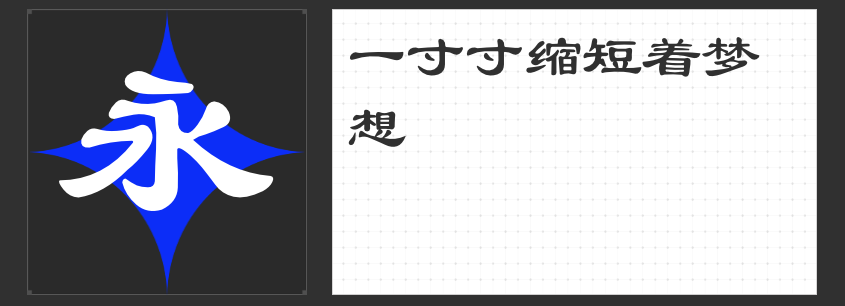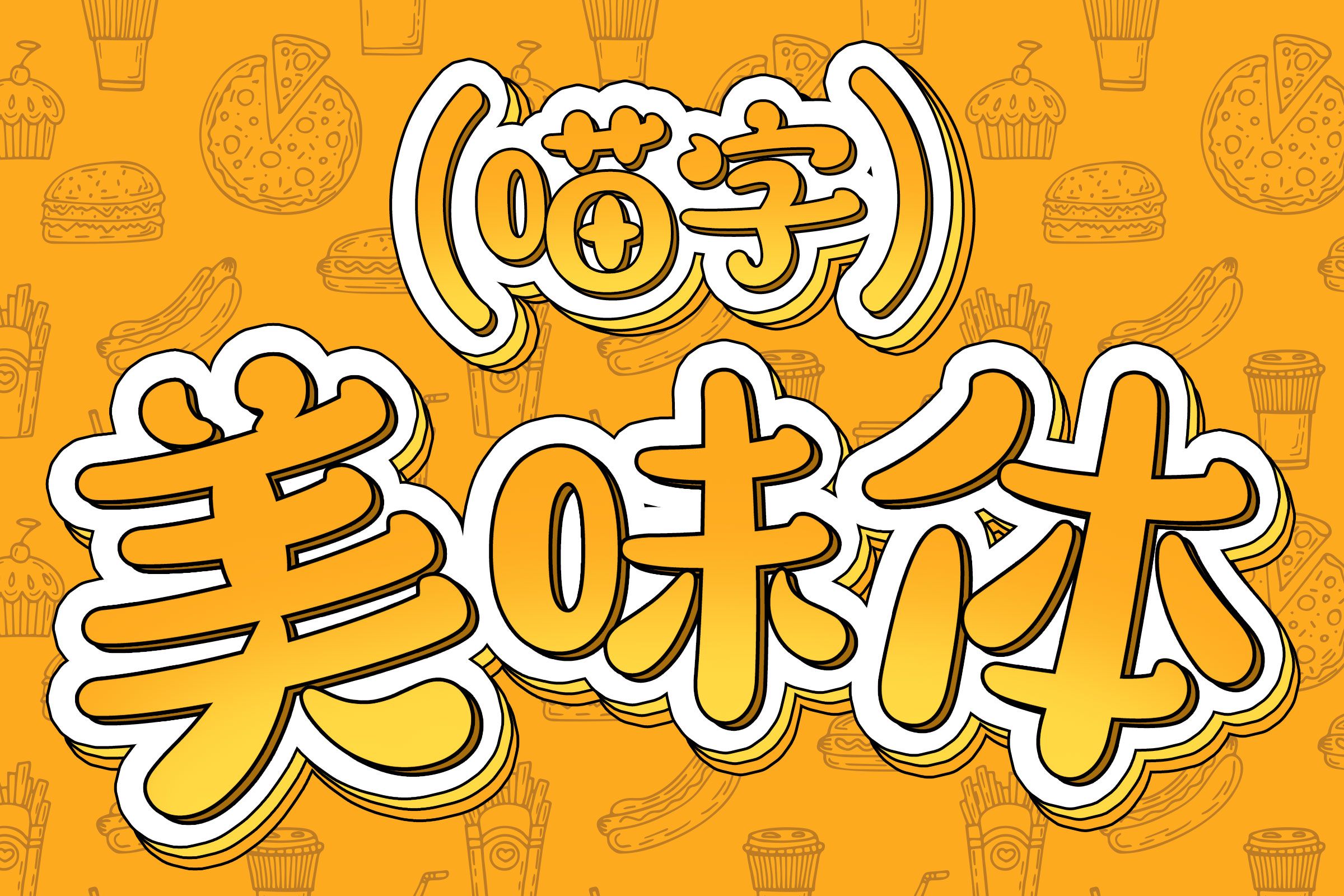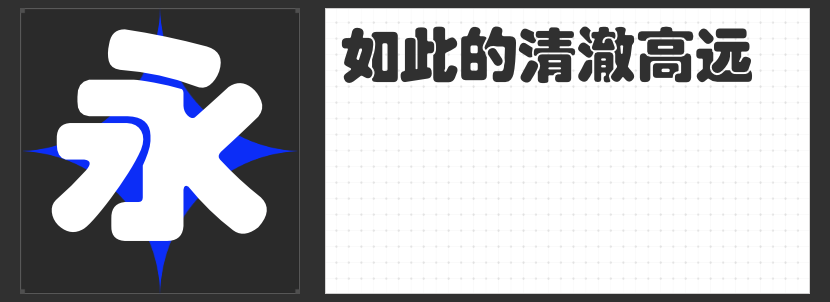
招牌设计的视觉密码:四款风格化字体赋能商业空间
招牌是商业空间的第一张名片,其字体选择直接影响品牌记忆度与空间氛围营造。本文精选四款兼具艺术张力与功能适配性的专业字体,从传统书韵到现代创意,为不同业态的招牌设计提供多元解决方案。
一、励字舒体简繁
这款融合五体书风与颜柳筋骨的创意字体,以0.8:1的字面率构建出独特的视觉韵律。其笔画粗细对比达1:3.5,在保持传统书法韵味的同时,通过现代参数化设计优化了远距离识别性。特别适合茶文化空间、文创书店等场景。
二、喵字美味体
专为美食空间开发的圆润字体,通过0.6pt的圆角半径处理与15°的笔画倾斜角,创造出类似食物饱满形态的视觉联想。其字怀(笔画内部空间)比常规字体扩大20%,在较远观看距离下仍保持清晰可读性。
三、励字琥珀简繁
这款圆润而不失力度的标题字体,其X字高与Y字高比例为1:1.2,在横向空间中形成稳定的视觉重心。0.4mm的笔画末端收尖处理,既保留了手写温度又符合现代审美。特别适合商场导视、连锁品牌招牌等需要强识别性的场景。
四、励字隶书简繁
通过解构汉代碑刻形成的扁方字体,其横竖笔画粗细比达到1:2.8,在纵向空间中形成独特的装饰张力。推荐用于传统文化会所、中医馆等场景,搭配青砖黛瓦与木质匾额,能完美复刻古雅意境。
这四款字体均经过专业视距测试与材质适配性优化。它们不仅是文字载体,更是连接品牌基因与空间叙事的视觉媒介,在商业竞争的红海中为招牌设计注入差异化竞争力。